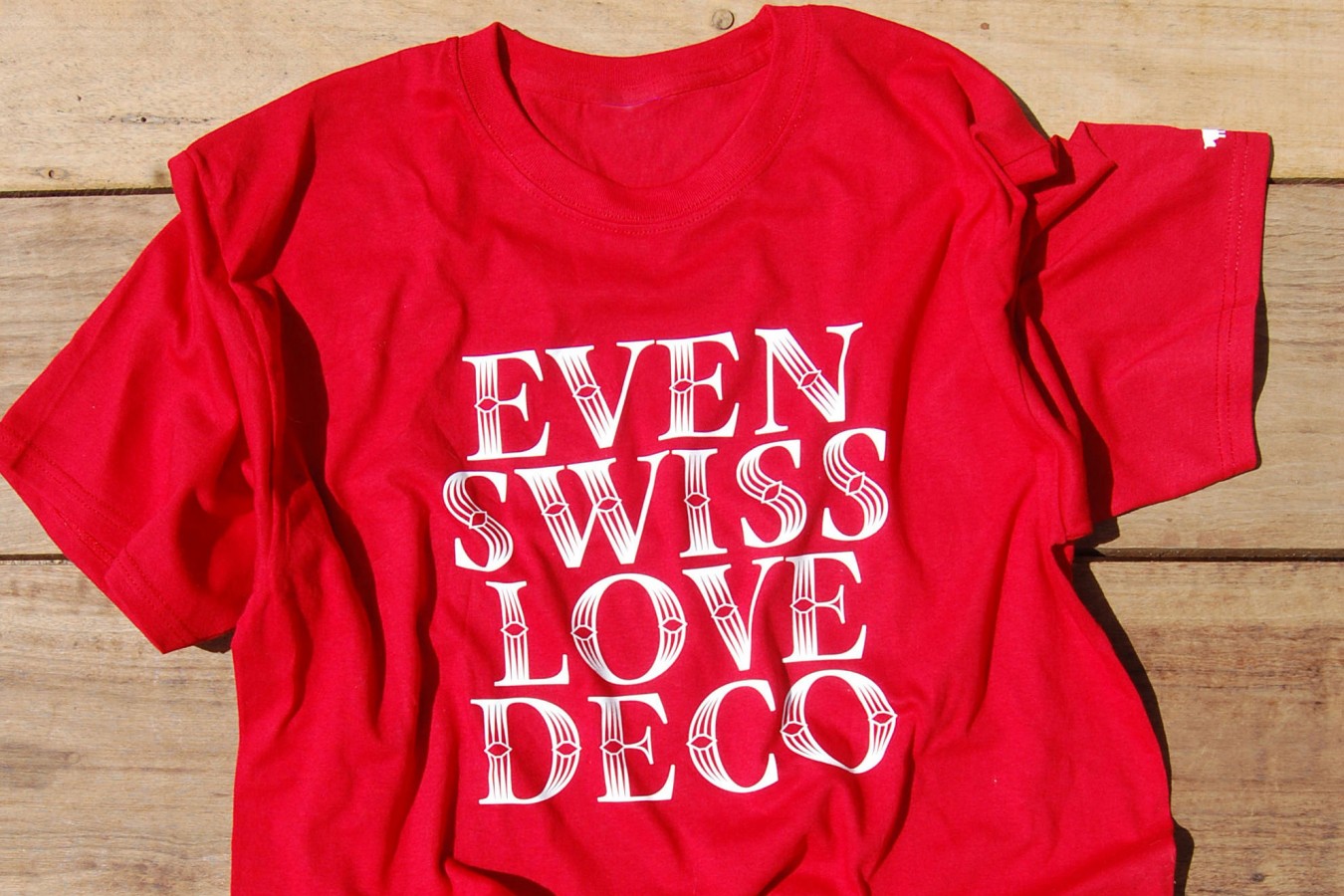
Camiseta
Even Swiss Love Deco
“Aun los suizos aman lo deco” es un pequeño homenaje a la pasión suiza por la tipografía. La escuela helvética de diseño contribuyó seriamente al movimiento moderno en la década de 1960. Los diseñadores suizos fueron famosos por adoptar reglas estrictas en favor de la austeridad de la forma. Muchos de ellos odiaban la idea de “lo decorativo”, asociado a la época victoriana. La escena del mundo ha cambiado mucho desde entonces, pero aun nos gusta la idea de los suizos como guardianes del Modernismo.